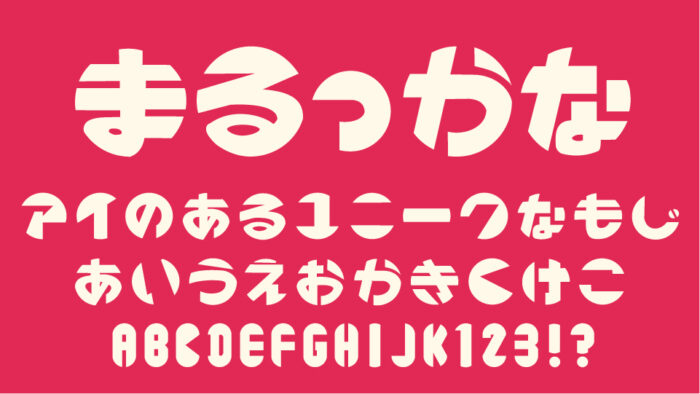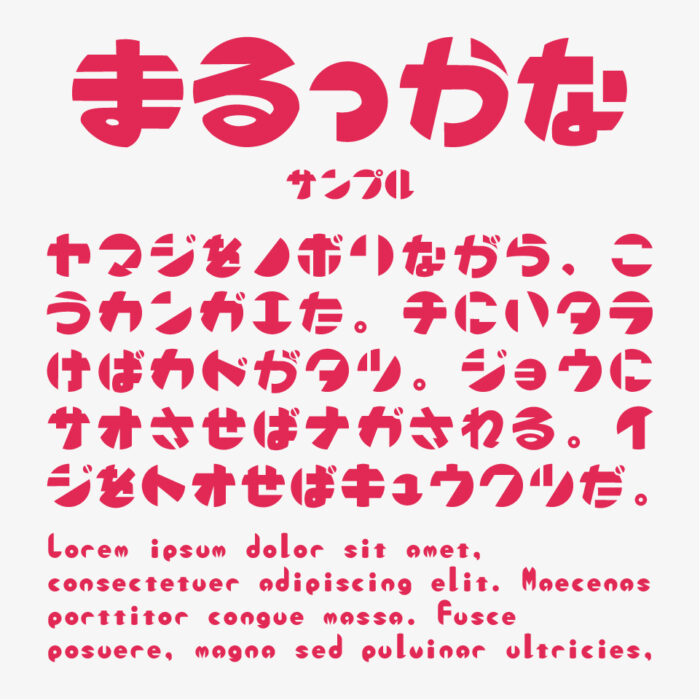
まるっかな
まるっかなフォントは、丸や長丸から削って制作されたデザインフォントです。
正円や長円をベースに、削ぎ落とすようにエッジを切り取った独特のシルエットが印象的なフォントとなっています。一般的なフォントとは制作手法が異なるので、まるっかなフォントならではの独自の面白いデザインです。
文字を並べてときの丸くてコロンッとしたシルエットは、とってもかわいいフォントとなっています。
収録文字は、ひらがな・カタカナ・アルファベット・数字・記号が収録されています。